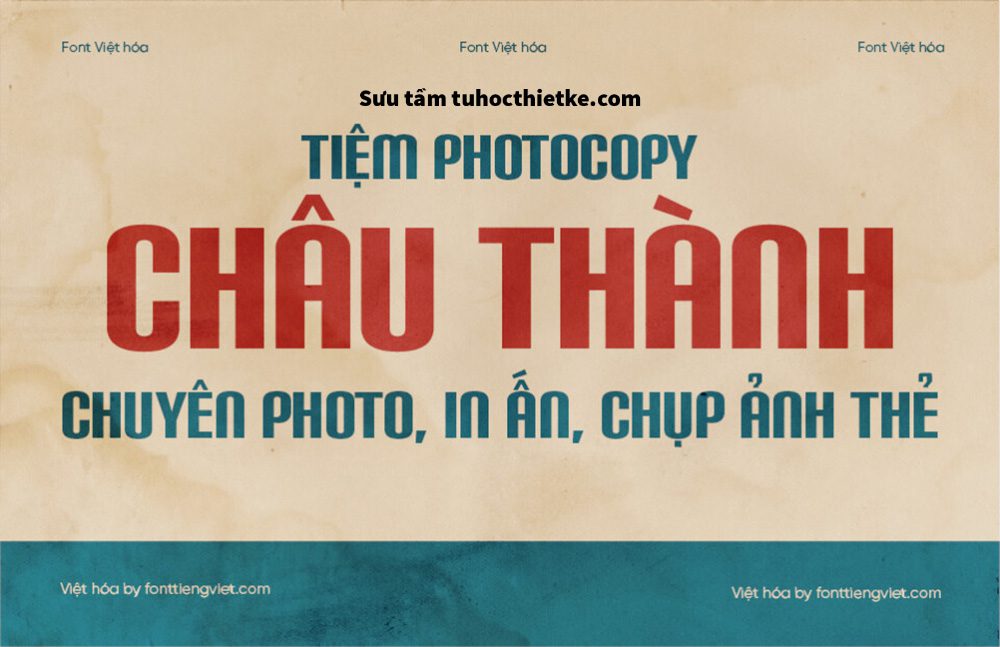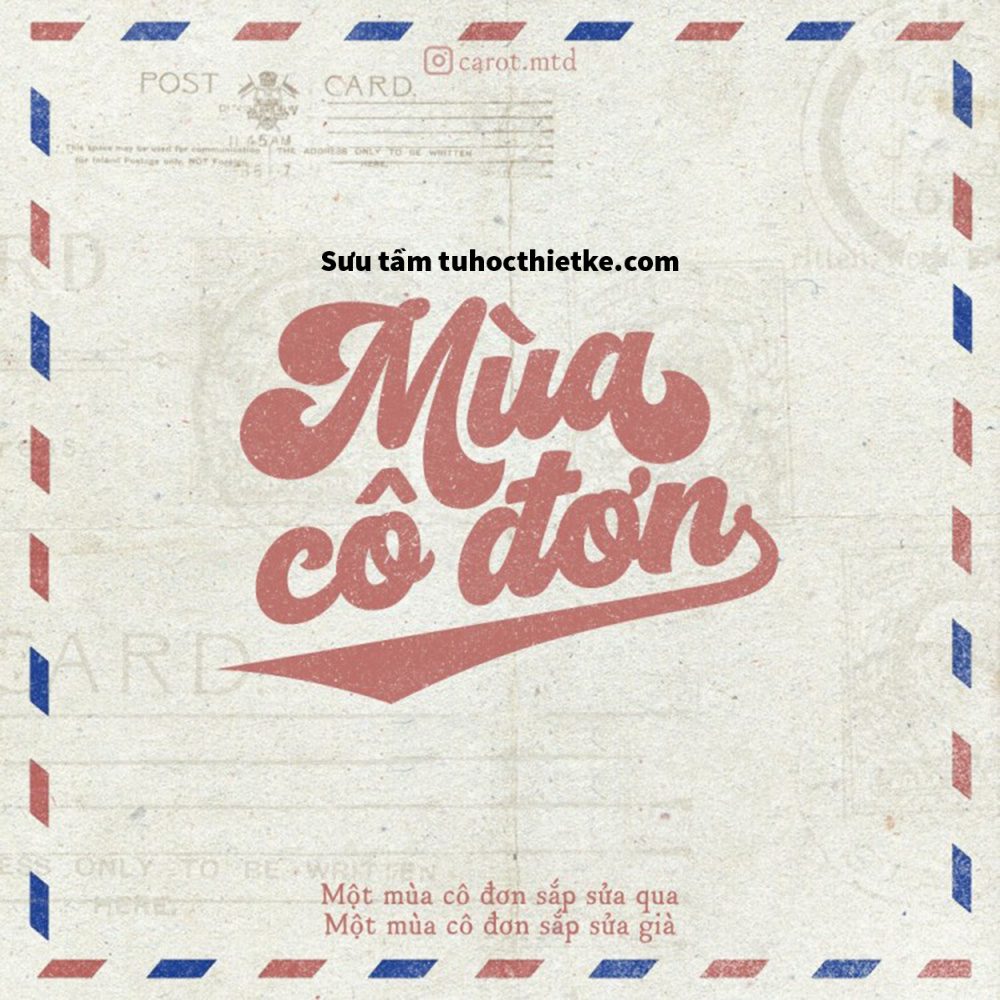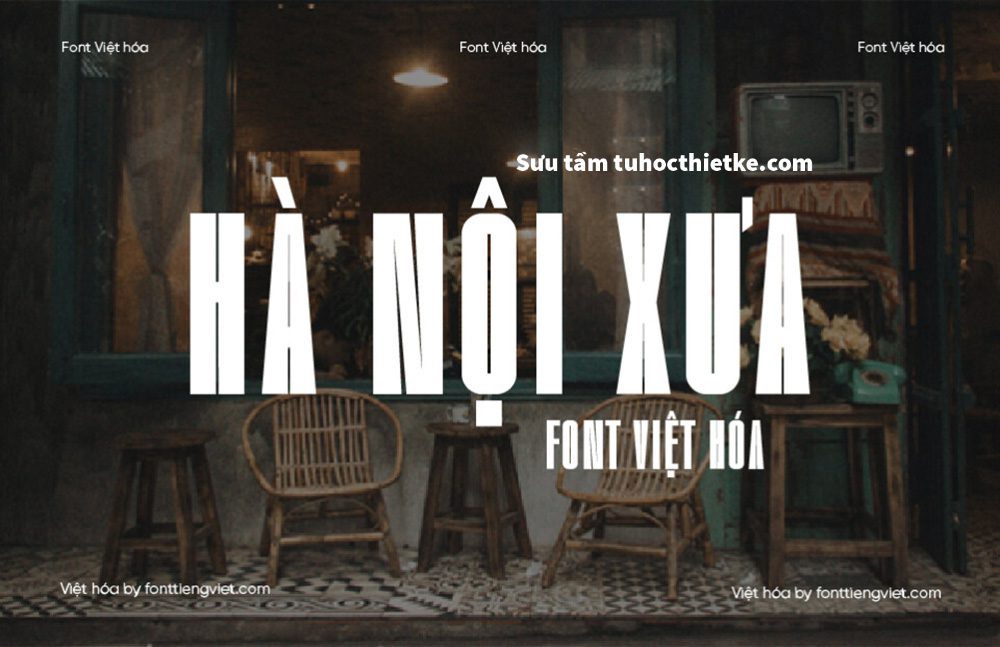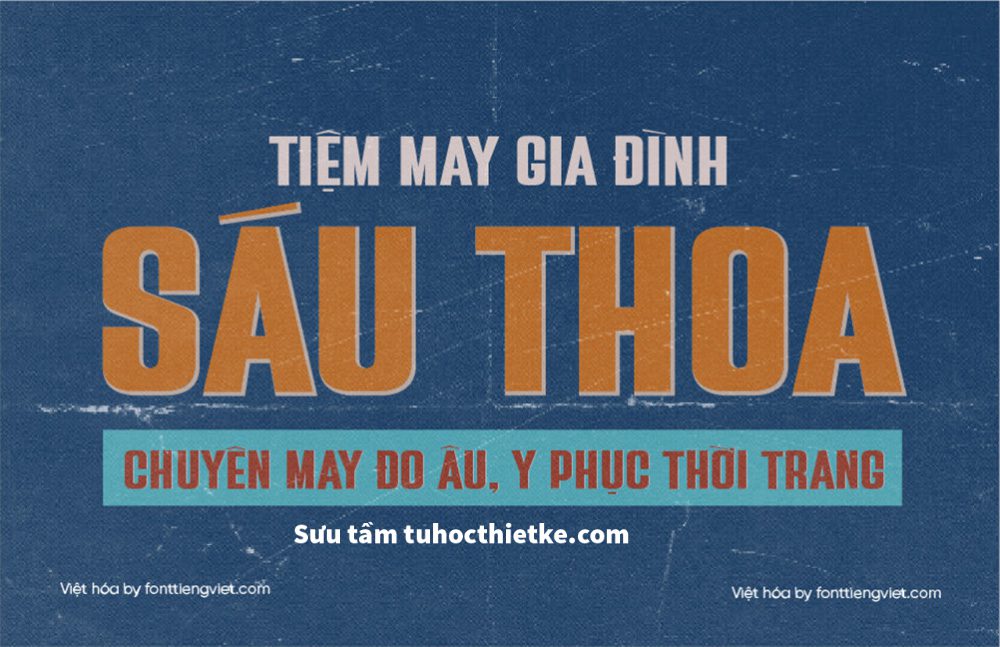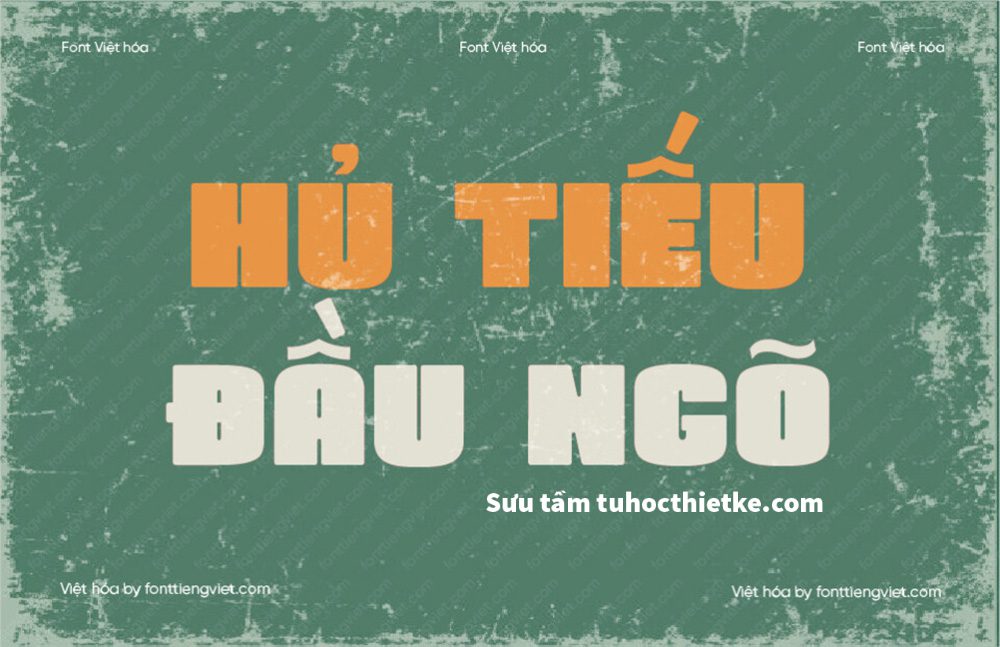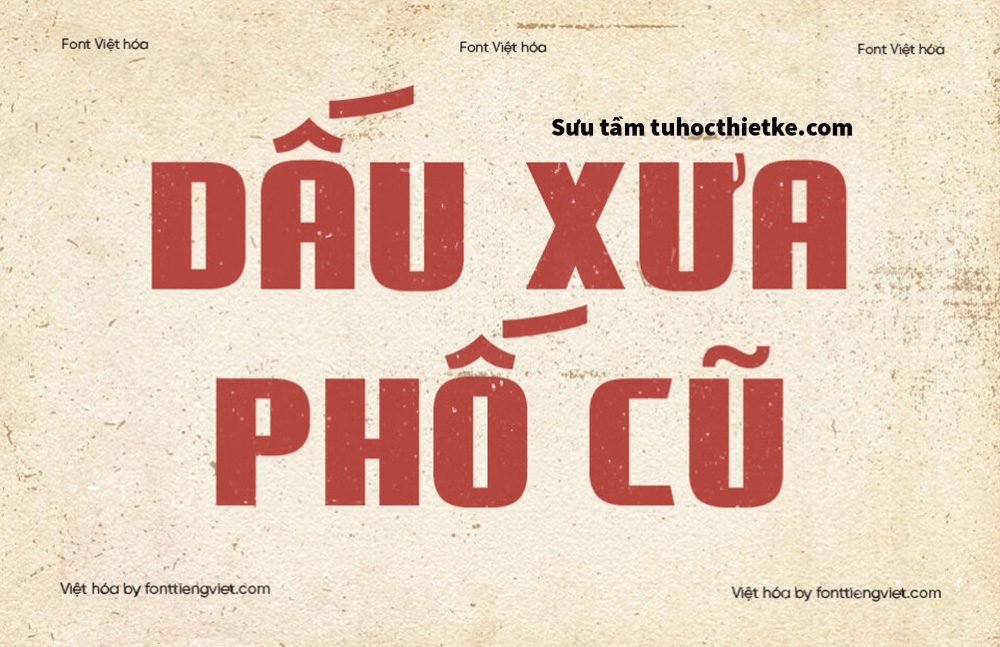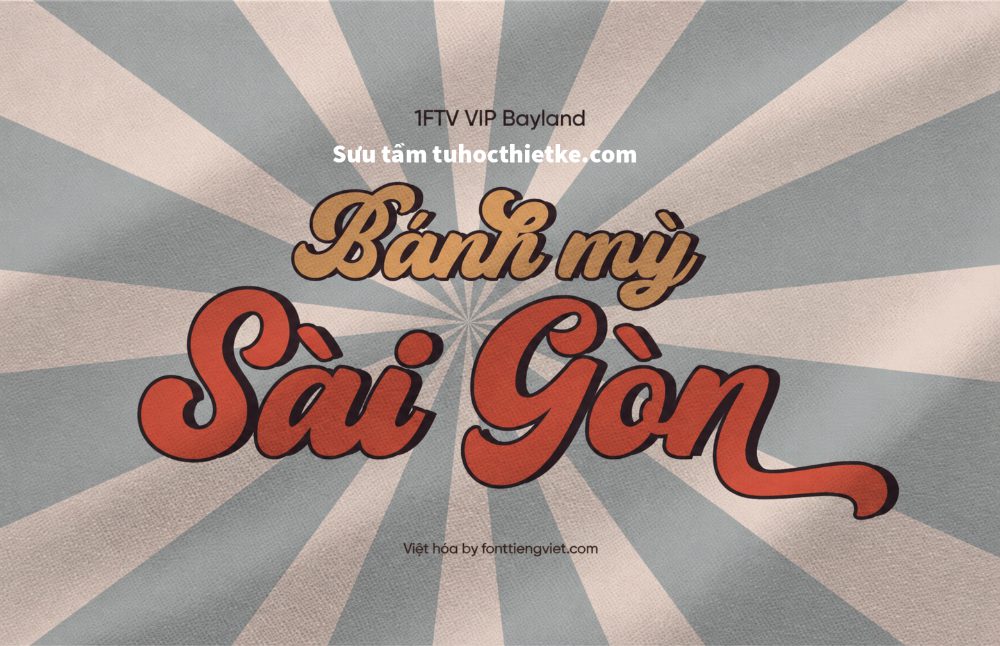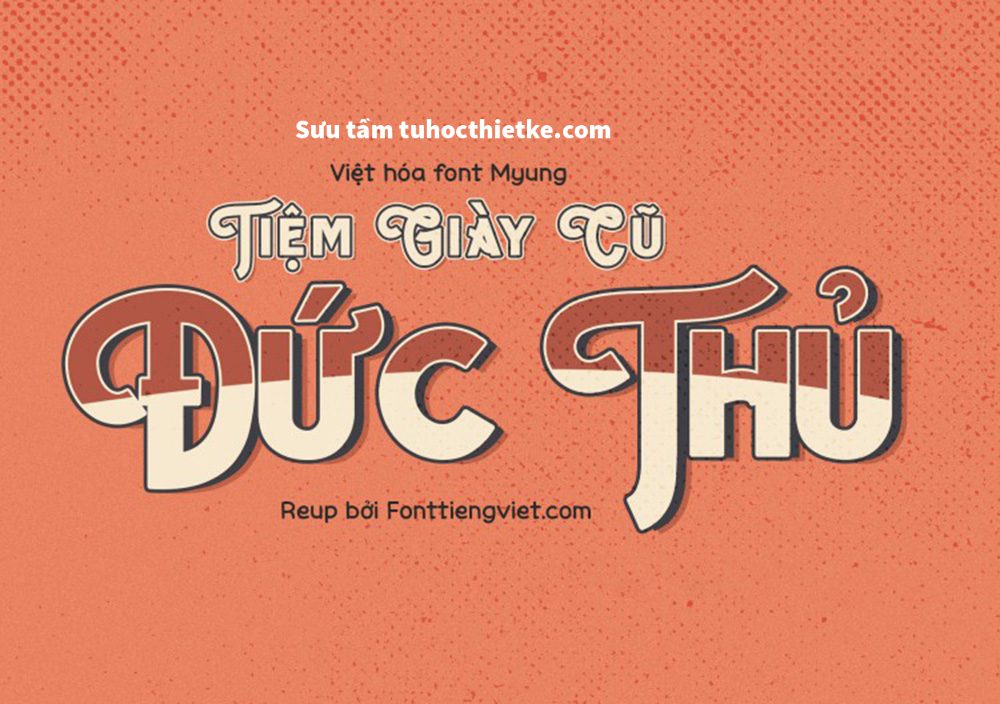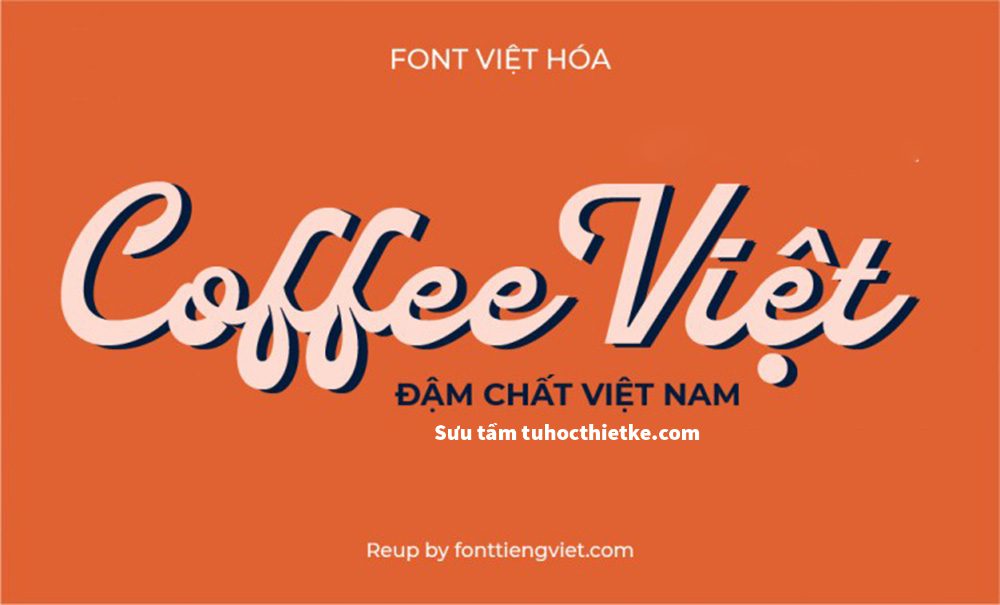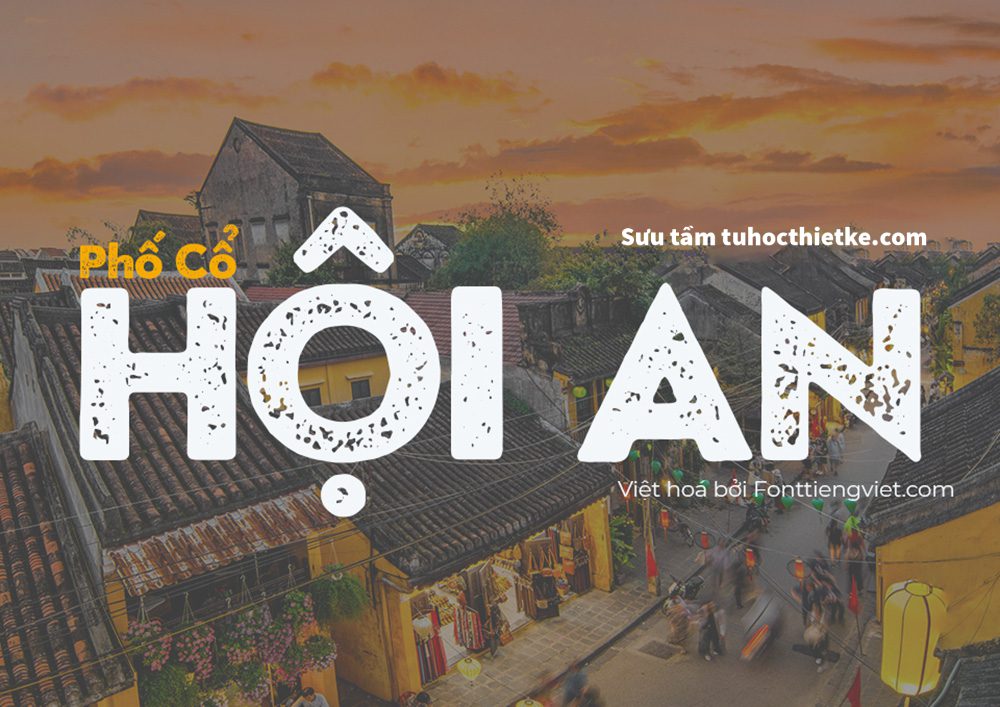
Trong thiết kế đồ họa, font chữ không chỉ là công cụ truyền tải nội dung mà còn là yếu tố quan trọng tạo nên cảm xúc, phong cách và dấu ấn riêng cho từng sản phẩm. Đặc biệt với những dự án mang hơi hướng xưa cũ, cổ điển hoặc vintage, việc lựa chọn đúng kiểu chữ sẽ giúp tổng thể thiết kế trở nên cuốn hút và có chiều sâu hơn. Chính vì vậy, các bộ font hoài cổ việt hóa ngày càng được nhiều designer, content creator và người làm thương hiệu tìm kiếm để ứng dụng trong poster, logo, banner, bao bì, ấn phẩm truyền thông hay các dự án nghệ thuật cá nhân.
Font hoài cổ Việt hóa là gì?
Font hoài cổ Việt hóa là những bộ font mang phong cách cổ điển, retro hoặc vintage, đã được bổ sung đầy đủ dấu tiếng Việt để sử dụng thuận tiện trong các thiết kế dành cho người Việt. Khác với những font chữ hiện đại thường có đường nét tối giản, gọn gàng, font hoài cổ thường sở hữu kiểu dáng mềm mại, phá cách, có chút cũ kỹ hoặc gợi nhớ đến những bảng hiệu, tạp chí, poster quảng cáo, bao bì sản phẩm từ nhiều thập niên trước.
Điểm đặc biệt của dòng font này nằm ở khả năng gợi cảm xúc. Chỉ cần thay đổi kiểu chữ, một thiết kế đơn giản cũng có thể trở nên ấm áp, nghệ thuật và mang màu sắc thời gian rõ rệt hơn. Đây là lý do các font vintage Việt hóa thường được sử dụng trong những dự án liên quan đến cà phê, thời trang, âm nhạc, mỹ phẩm handmade, nhà hàng, quán ăn, tiệm bánh, du lịch hoặc các sản phẩm mang tinh thần thủ công.
Vì sao nên sử dụng font hoài cổ Việt hóa trong thiết kế?
Hỗ trợ tiếng Việt đầy đủ
Một trong những vấn đề nhiều designer thường gặp khi dùng font nước ngoài là lỗi dấu tiếng Việt. Font có thể rất đẹp khi viết tiếng Anh, nhưng khi gõ tiếng Việt lại bị mất dấu, lệch dấu hoặc hiển thị không đồng đều. Với các bộ font đã được Việt hóa, bạn có thể dễ dàng sử dụng cho tiêu đề, slogan, nội dung quảng cáo hoặc nhận diện thương hiệu mà không lo lỗi hiển thị.
Điều này đặc biệt quan trọng với các thiết kế chuyên nghiệp. Một font chữ đẹp nhưng lỗi dấu sẽ làm giảm chất lượng tổng thể, khiến sản phẩm trông thiếu chỉn chu. Vì vậy, lựa chọn font hoài cổ việt hóa là giải pháp phù hợp nếu bạn muốn tạo ra các ấn phẩm vừa thẩm mỹ vừa dễ đọc đối với người xem Việt Nam.
Tạo cảm giác vintage rõ ràng
Phong cách vintage thường gắn liền với sự hoài niệm, gần gũi và giàu cảm xúc. Font chữ đóng vai trò rất lớn trong việc xây dựng tinh thần đó. Những đường nét cong nhẹ, chân chữ cổ điển, độ tương phản đậm nhạt hoặc hiệu ứng chữ viết tay có thể giúp thiết kế mang lại cảm giác như một tấm poster cũ, một nhãn hàng thủ công hoặc một ấn phẩm nghệ thuật từ thời trước.
Nếu bạn đang làm thiết kế theo chủ đề retro, classic, old school hoặc nostalgic, font hoài cổ sẽ giúp tiết kiệm rất nhiều thời gian trong quá trình định hình phong cách. Thay vì phải thêm quá nhiều hiệu ứng phức tạp, đôi khi chỉ cần chọn đúng font, phối màu phù hợp và sắp xếp bố cục hợp lý là thiết kế đã có thể truyền tải đúng tinh thần mong muốn.
Phù hợp với nhiều loại dự án sáng tạo
Font hoài cổ không chỉ dành riêng cho poster vintage. Bạn có thể dùng dòng font này cho rất nhiều hạng mục khác nhau như logo thương hiệu, ảnh bìa website, thumbnail YouTube, bài đăng mạng xã hội, thiệp mời, menu quán cà phê, bao bì sản phẩm, nhãn dán, catalogue hoặc banner quảng cáo.
Đối với các thương hiệu muốn xây dựng hình ảnh gần gũi, thủ công, truyền thống hoặc mang tính nghệ thuật, font hoài cổ là lựa chọn rất đáng cân nhắc. Nó giúp thương hiệu trở nên khác biệt hơn so với những thiết kế dùng font hiện đại phổ biến.
Gợi ý cách sử dụng font hoài cổ Việt hóa hiệu quả
Dùng cho tiêu đề nổi bật
Font hoài cổ thường có cá tính mạnh, vì vậy phù hợp nhất khi dùng cho tiêu đề chính, tên thương hiệu, headline hoặc các câu slogan ngắn. Khi đặt ở vị trí nổi bật, font sẽ phát huy tốt khả năng thu hút ánh nhìn và tạo điểm nhấn cho bố cục.
Tuy nhiên, bạn không nên sử dụng font quá cầu kỳ cho toàn bộ đoạn văn dài. Những kiểu chữ có nhiều chi tiết trang trí có thể gây khó đọc nếu dùng quá nhiều. Cách tốt nhất là kết hợp font hoài cổ với một font phụ đơn giản để tạo sự cân bằng.
Kết hợp màu sắc vintage
Để font phát huy đúng tinh thần hoài cổ, màu sắc đi kèm cũng rất quan trọng. Bạn có thể sử dụng các gam màu như nâu đất, kem, vàng nhạt, đỏ gạch, xanh rêu, cam cháy hoặc đen ngà. Những màu này thường tạo cảm giác cũ kỹ, ấm áp và gần gũi hơn so với các màu neon hoặc màu quá rực.
Ngoài ra, có thể kết hợp thêm texture giấy cũ, hiệu ứng noise, hạt film, viền mòn hoặc nền retro để tăng chiều sâu cho thiết kế. Khi font chữ, màu sắc và chất liệu hình ảnh đồng nhất, tổng thể sản phẩm sẽ chuyên nghiệp và có cảm xúc hơn.
Chú ý khoảng cách chữ và bố cục
Một số font hoài cổ có ký tự khá rộng hoặc nét chữ nhiều chi tiết, vì vậy bạn nên kiểm tra kỹ khoảng cách giữa các chữ, dòng và khối văn bản. Nếu chữ quá sát nhau, thiết kế dễ bị rối. Ngược lại, nếu khoảng cách quá xa, nội dung có thể mất sự liên kết.
Khi thiết kế poster hoặc banner, hãy ưu tiên bố cục rõ ràng. Font hoài cổ nên được đặt ở vị trí trung tâm hoặc khu vực có nhiều khoảng trống để người xem dễ tập trung vào nội dung chính. Không nên đặt chữ lên nền quá nhiều chi tiết vì sẽ làm giảm khả năng đọc.
Nếu biết kết hợp hợp lý giữa kiểu chữ, màu sắc, hình ảnh và bố cục, bạn hoàn toàn có thể tạo ra những ấn phẩm đẹp mắt, chuyên nghiệp và phù hợp với tinh thần vintage. Hãy chọn cho mình những bộ font chất lượng, kiểm tra kỹ quyền sử dụng và ứng dụng sáng tạo để mỗi thiết kế đều mang một câu chuyện riêng.